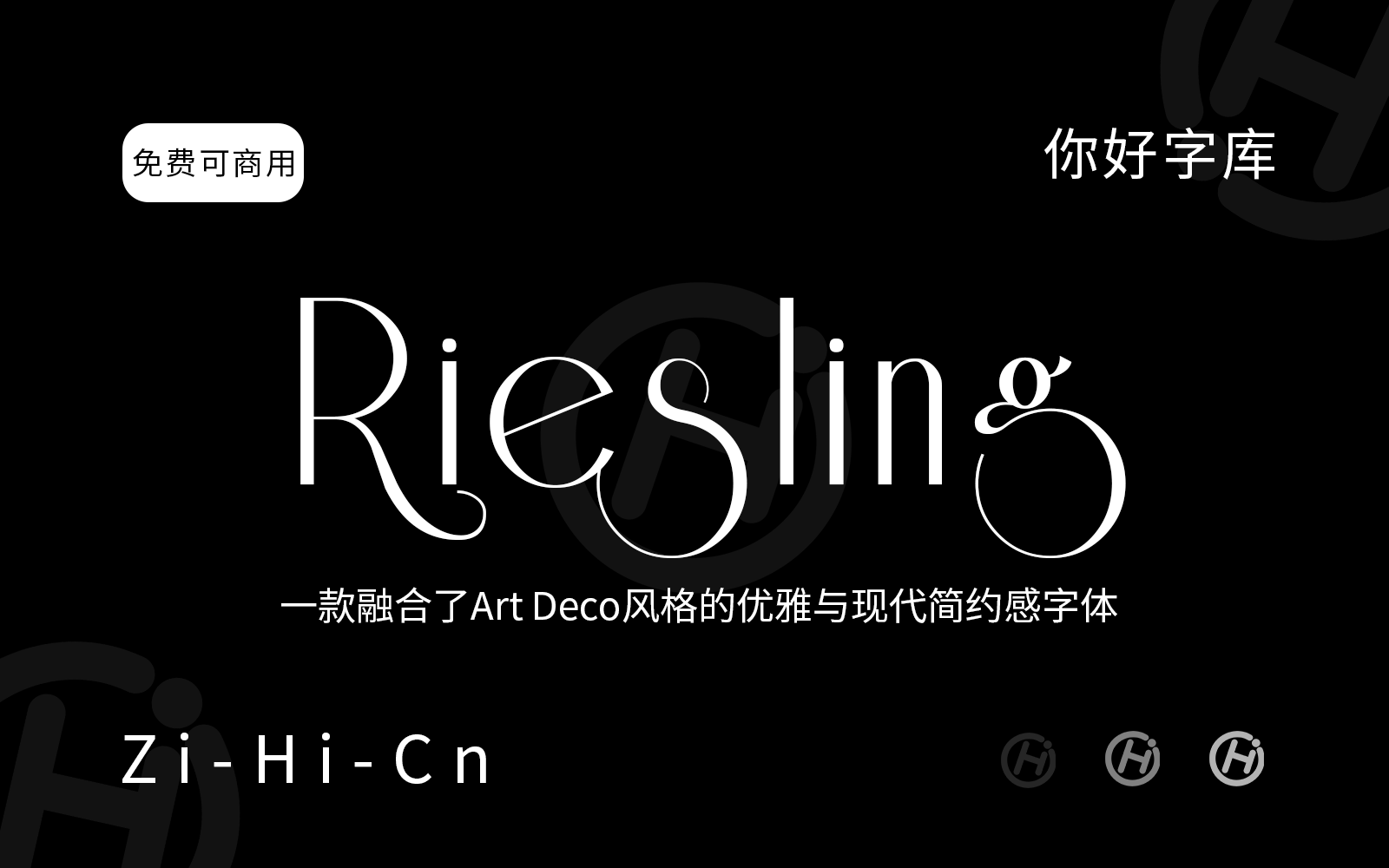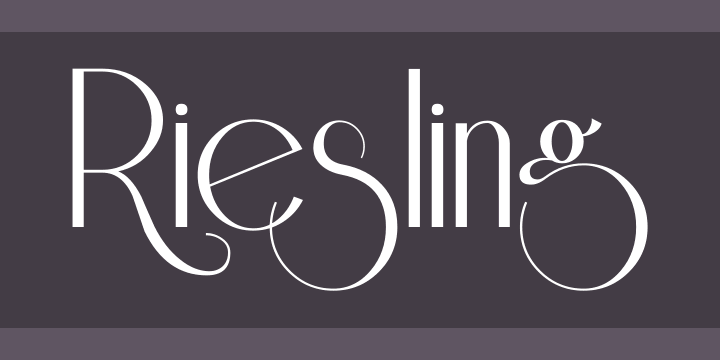
Riesling
“Riesling”是一款由 Bright Ideas 设计的免费衬线字体,首次发布于2008年5月17日。它属于装饰性字体(Fancy > Retro),灵感源自20世纪中期的复古广告和招牌设计,融合了Art Deco风格的优雅与现代简约感。字形纤细修长,线条流畅,带有微妙的曲线和几何感,适合营造精致、怀旧的视觉效果。
Riesling 包含234个字形,支持大写和小写拉丁字母、数字、标点符号及部分多语言字符,但不支持中日韩(CJK)字符。